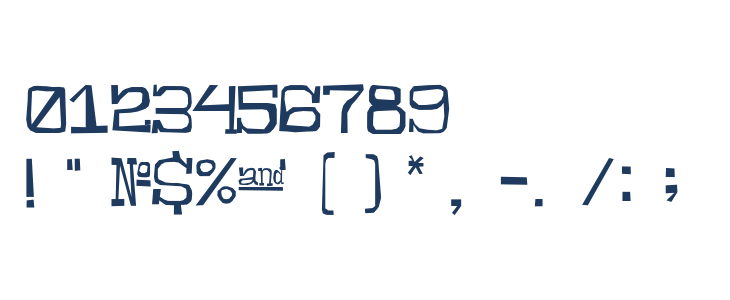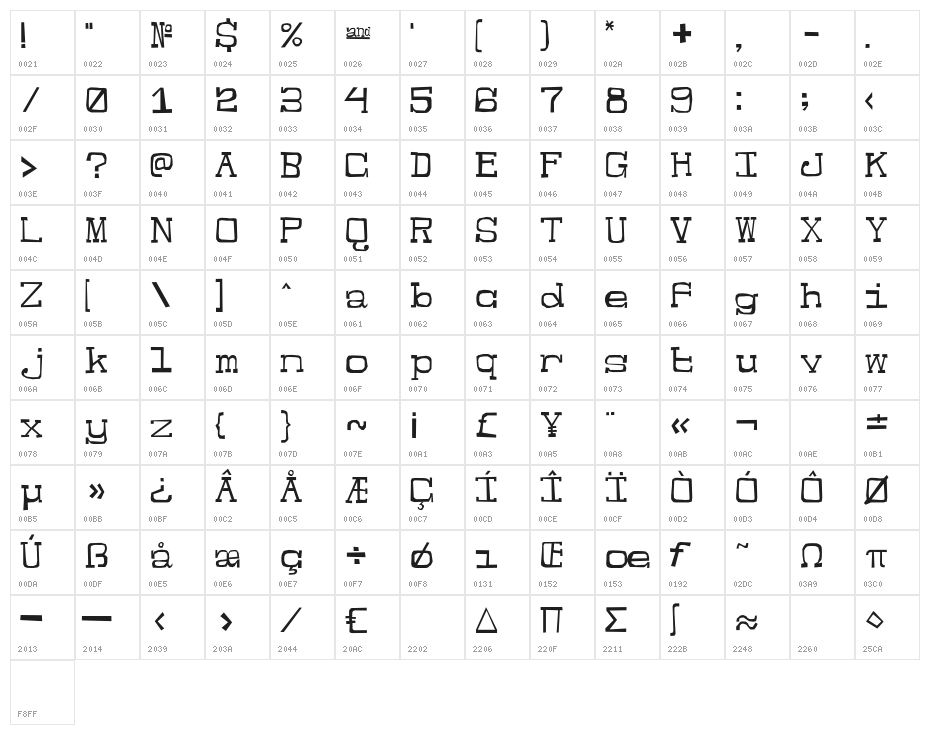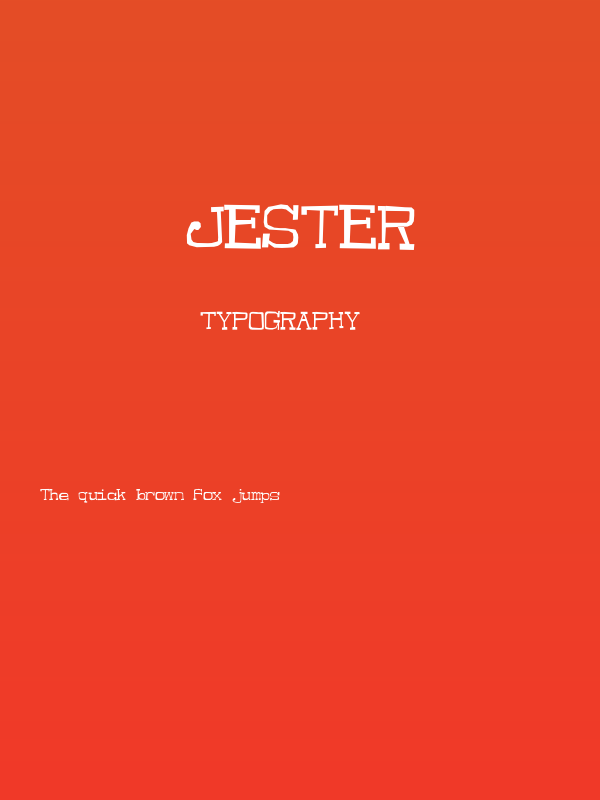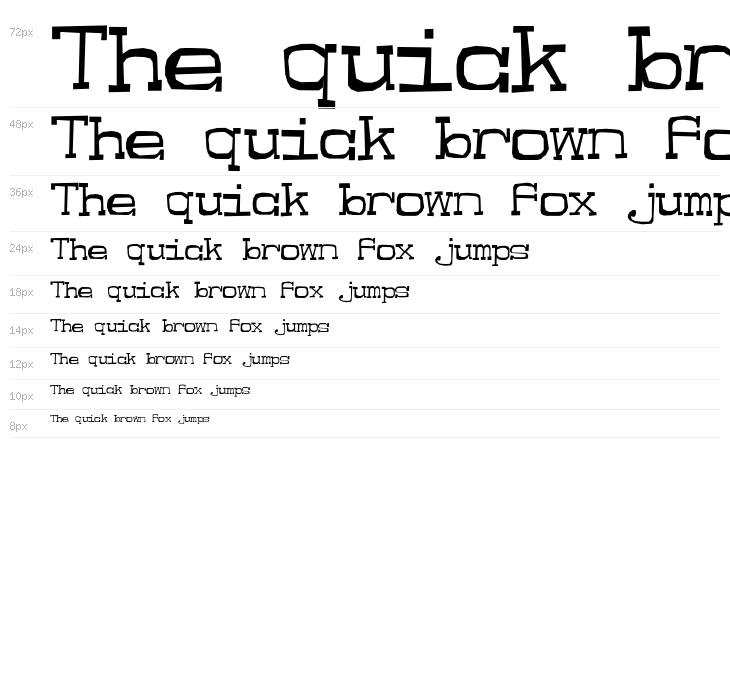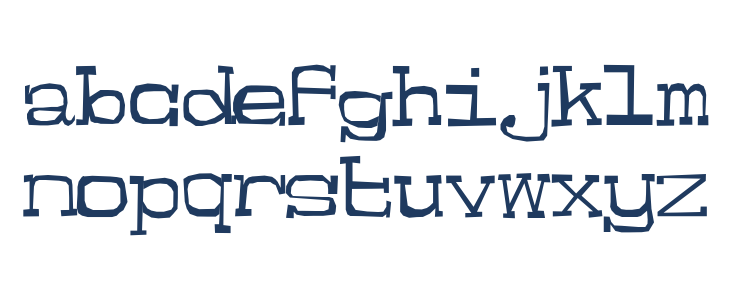
Jester Font
✎ Cartoon
| Kategorien | Cartoon |
| Gesamtstil | Playful |
| Vorgeschlagene Projekte | Ideal for children's books, playful branding, party invitations, and creative posters. |